올해 상반기 산돌구름에서 주목받은 4개의 신규 무료폰트를 추천해 보려고 합니다.
이 글에서 다루는 6가지 핵심 내용
- 2026년 상반기 주목받은 상업용 무료폰트 4종 소개
- 에이투지체의 9가지 굵기와 제목·본문 모두 쓰기 좋은 모던 고딕 활용법
- KBL 코트체의 굵고 역동적인 인상과 스포츠·이벤트 타이틀 활용 포인트
- 그리운 체리한스푼의 동글동글 달콤한 감성과 귀여운 콘텐츠 활용 팁
- 대구북성로의 무게감 있는 분위기와 레트로·지역 감성 연출 팁
「에이투지체」
단정하고 균형 잡힌 모던 고딕
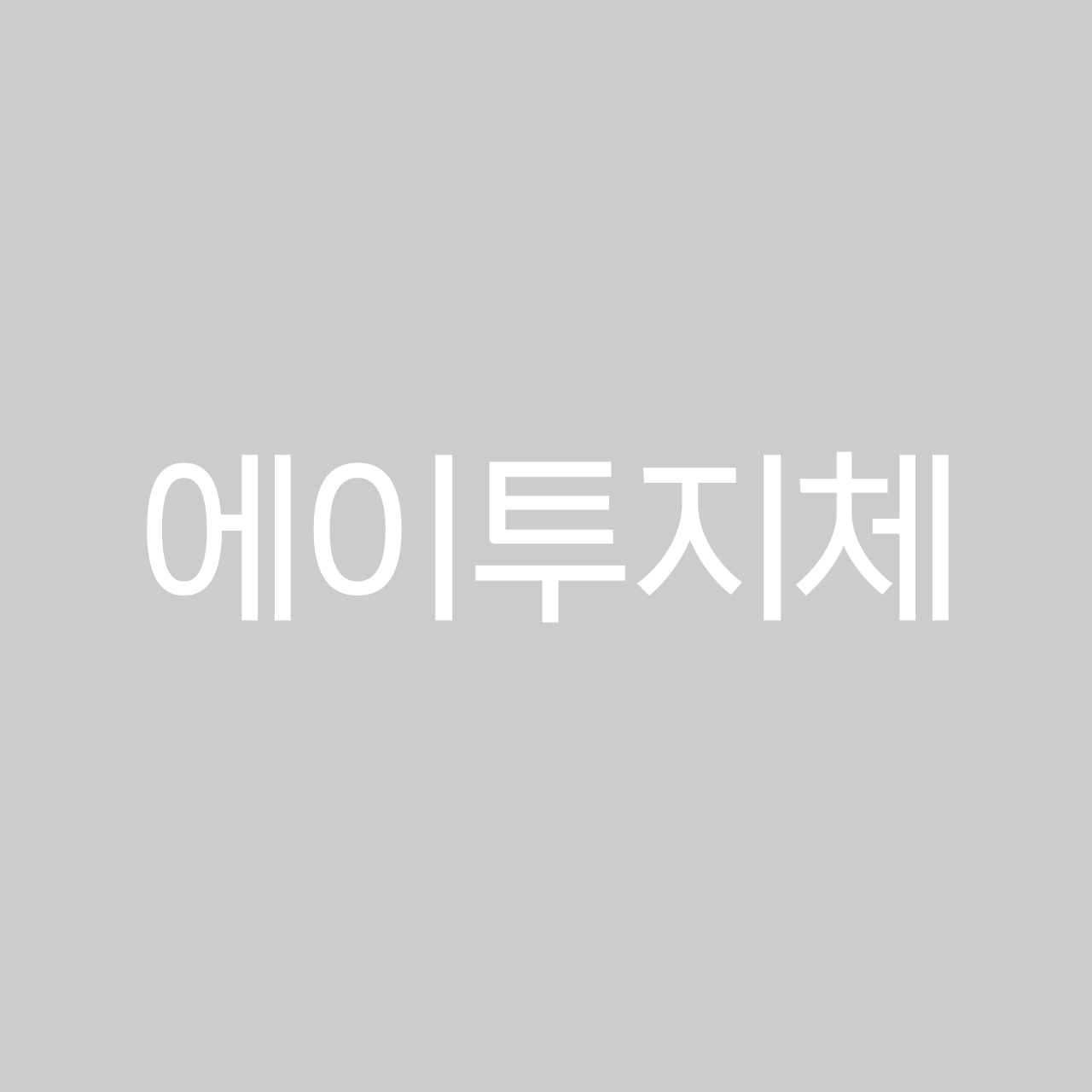
「에이투지체」는 자율주행 기업 오토노머스에이투지가 만든 전용 서체예요
부드러운 곡선과 절제된 사선이 어우러져
깔끔하면서도 미래적인 인상을 준답니다
Thin부터 Black까지 무려 9가지 굵기를 제공해서
제목과 본문을 한 폰트로 통일하기 좋아요
「KBL 코트체」
코트 위의 에너지를 그대로!
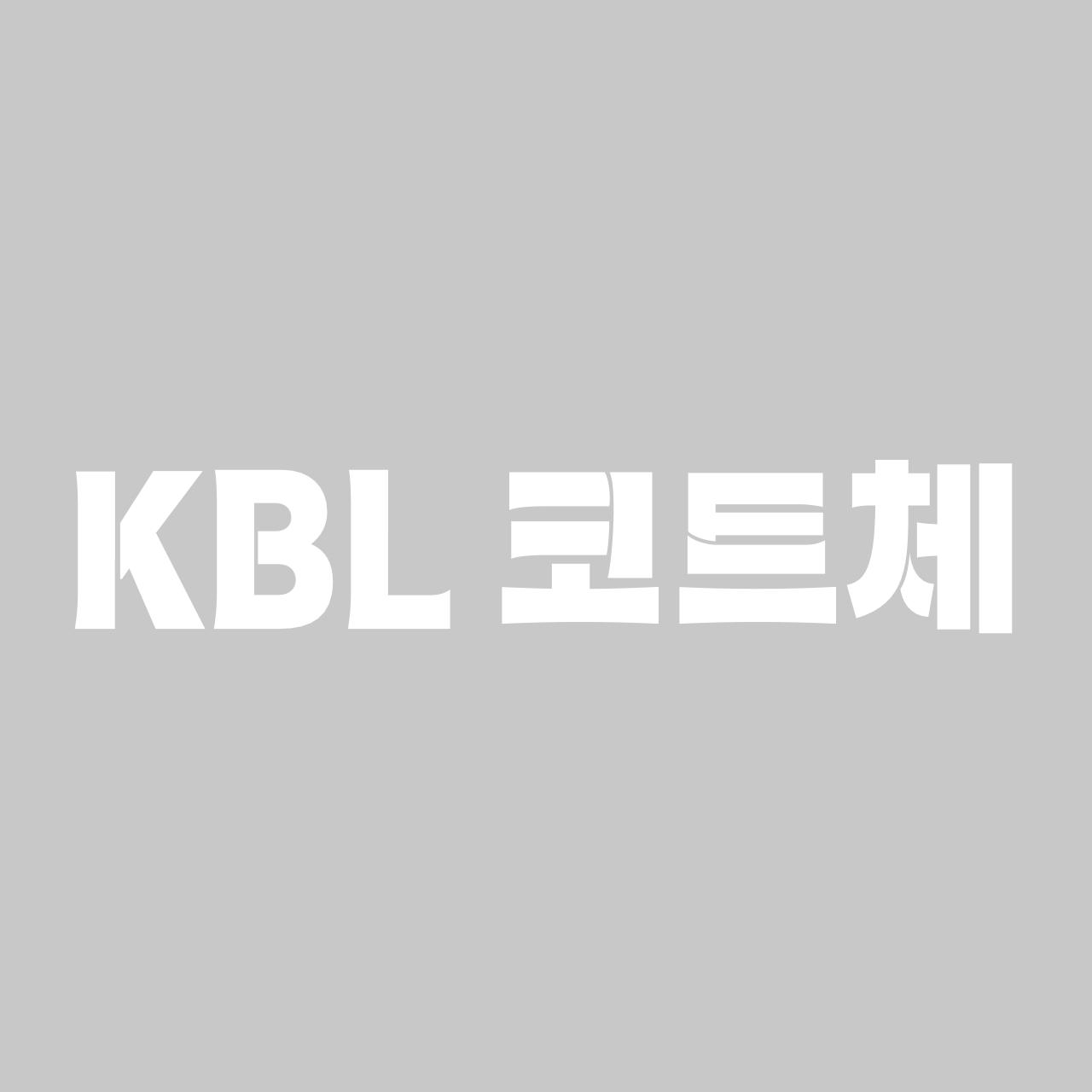
「KBL 코트체」는 한국프로농구연맹(KBL)이 선보인 전용 서체예요
굵고 직선적인 획이 역동적인 인상을 만들어
한눈에 시선을 사로잡아요
ExtraBold 한 가지 굵기로 존재감이 확실해서
스포츠, 이벤트, 프로모션 타이틀에 쓰면 제격이겠네요!
강렬한 한 줄 카피가 필요할 때 추천해요.
「그리운 체리한스푼」
일상에 달콤함 한 스푼
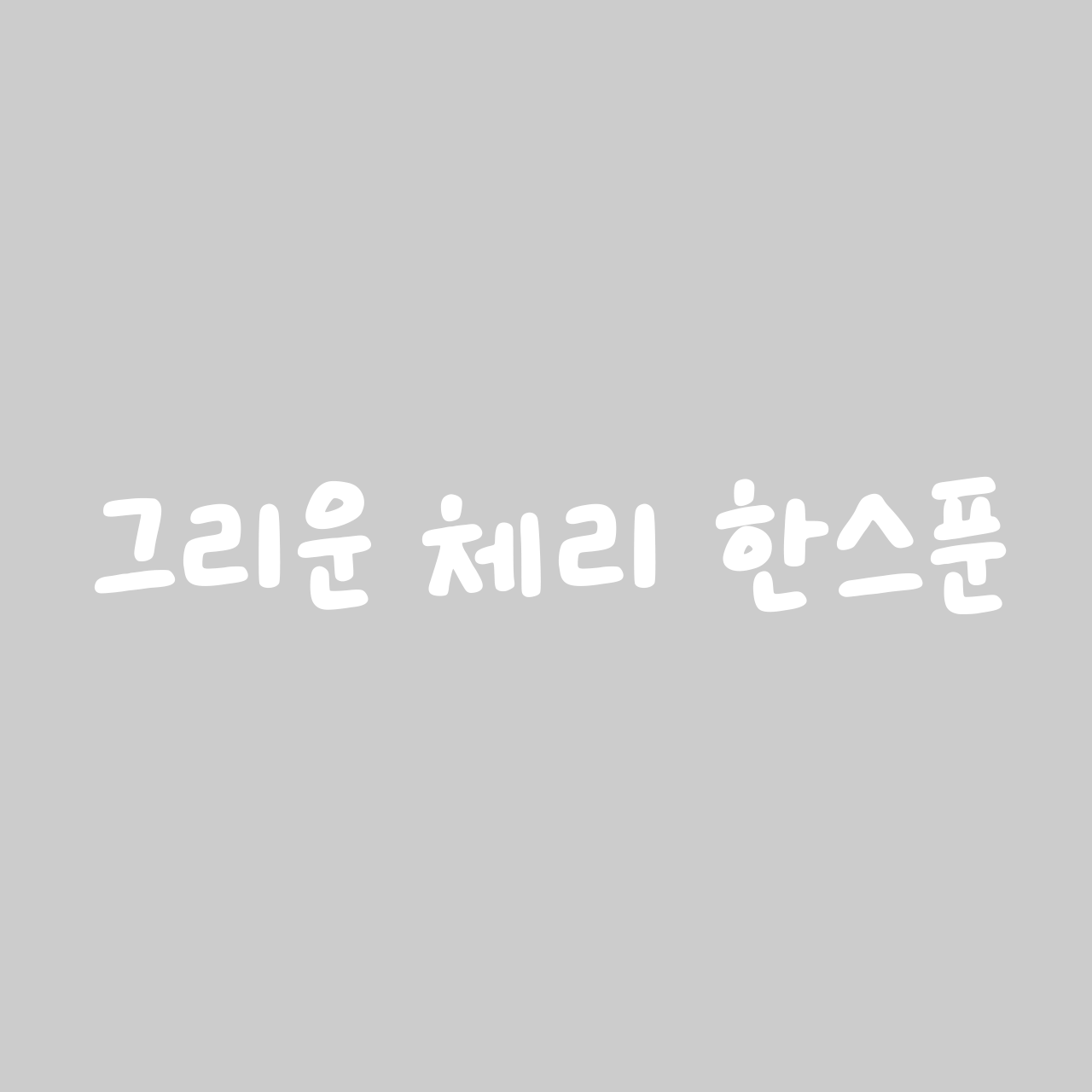
이름만 들어도 달콤한 느낌이 들지 않나요?
「그리운 체리한스푼」은 도톰하고 일정한 굵기에 둥글둥글한 곡선을 더해
통통 튀는 발랄함과 친근한 인상을 담은 손글씨 폰트예요
동글동글 귀여운 글자에 도톰한 굵기까지 더해져
시인성도 놓치지 않았답니다!
브이로그, 디저트, 굿즈처럼 귀엽고 따뜻한 콘텐츠라면 이 폰트 추천!
「대구북성로」
골목의 역사를 담은 묵직한 멋
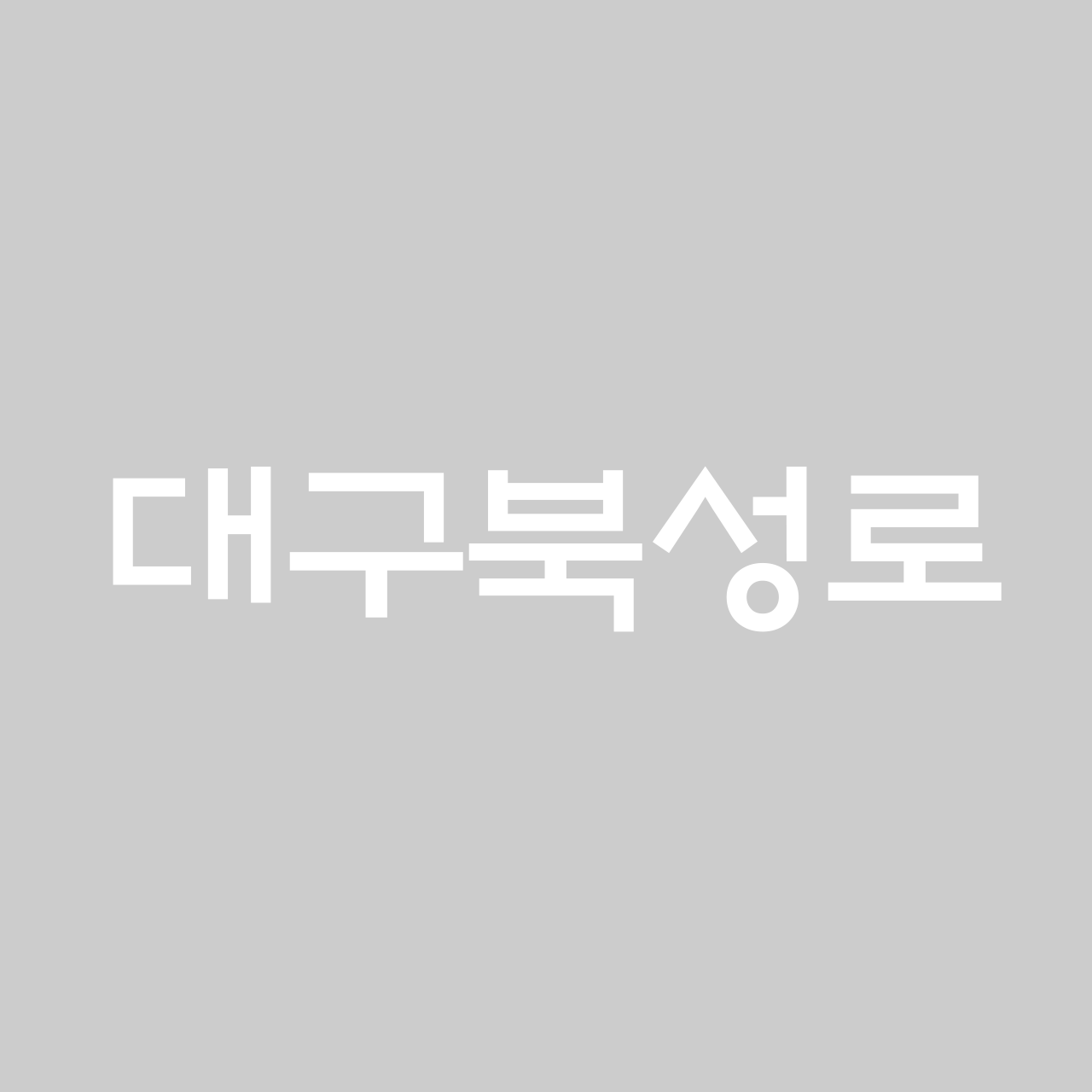
「대구북성로」는 대구광역시 중구청이 만든 지역 전용 서체예요
북성로의 역사적 자산과 현대적 감각을 결합해
전통적이고 무게감 있는 분위기를 연출해요
정원형에 가까운 동그란 ‘ㅇ’이 포인트!
Light와 ExtraBold 두 가지 굵기로
레트로 포스터나 공간·지역 콘텐츠에 멋스럽게 활용해 보세요!
Q&A
Q. 2026년 상반기에는 어떤 무료폰트가 주목받았나요?
산돌구름에서는 모던 고딕 「에이투지체」, 역동적인 디스플레이 폰트 「KBL 코트체」, 귀여운 손글씨 「그리운 체리한스푼」, 지역 감성을 담은 「대구북성로」 등 기업·기관이 만든 전용 서체가 신규 무료폰트로 많은 관심을 받았어요.
Q. 용도에 따라 어떤 폰트를 고르면 좋나요?
제목과 본문을 통일하고 싶다면 「에이투지체」, 강렬한 타이틀이 필요하다면 「KBL 코트체」, 귀엽고 따뜻한 콘텐츠엔 「그리운 체리한스푼」, 무게감 있는 레트로 무드엔 「대구북성로」가 잘 어울려요. 콘텐츠의 톤과 폰트의 인상을 맞추는 것이 핵심이에요.